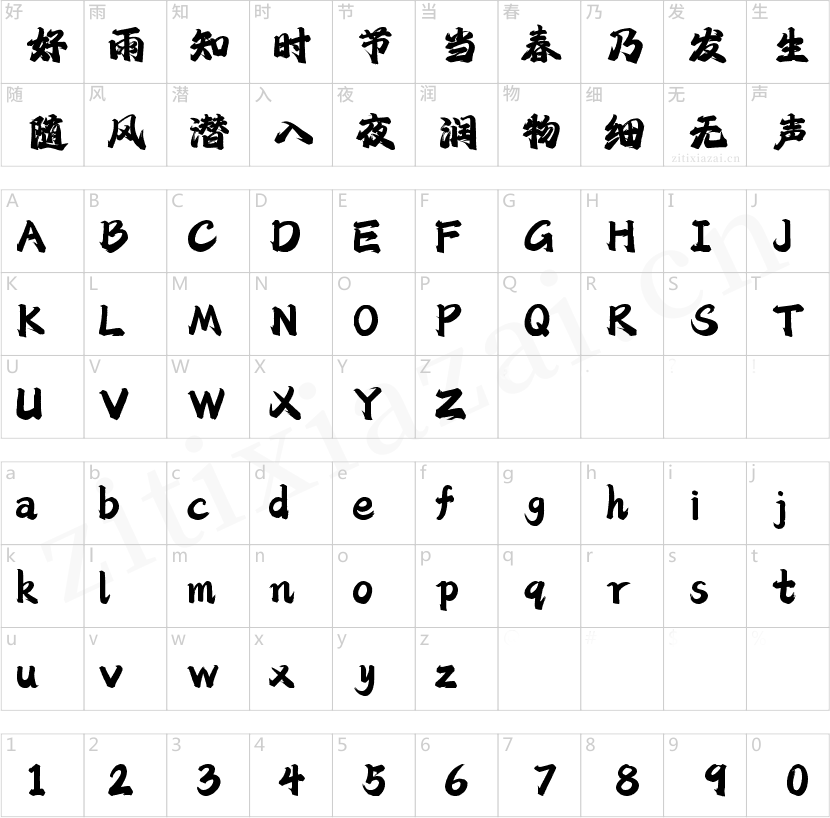
字魂武术体
字魂武术体,这款字体结构工整、笔画清晰,兼顾美观与易读性,适用于标题、正文、海报、包装、LOGO 等多种场景。字形优雅稳定,风格百搭耐看,适配日常排版与创意设计,让文字呈现更舒适、更具质感。字魂武术体一笔一画,皆是细节,以均衡的比例、流畅的线条打造舒适视觉体验,字形端正大气,风格简约现代。无论是商业设计、品牌宣传还是日常排版,都能轻松驾驭,让文字更有格调与力量。字魂武术体字体下载。